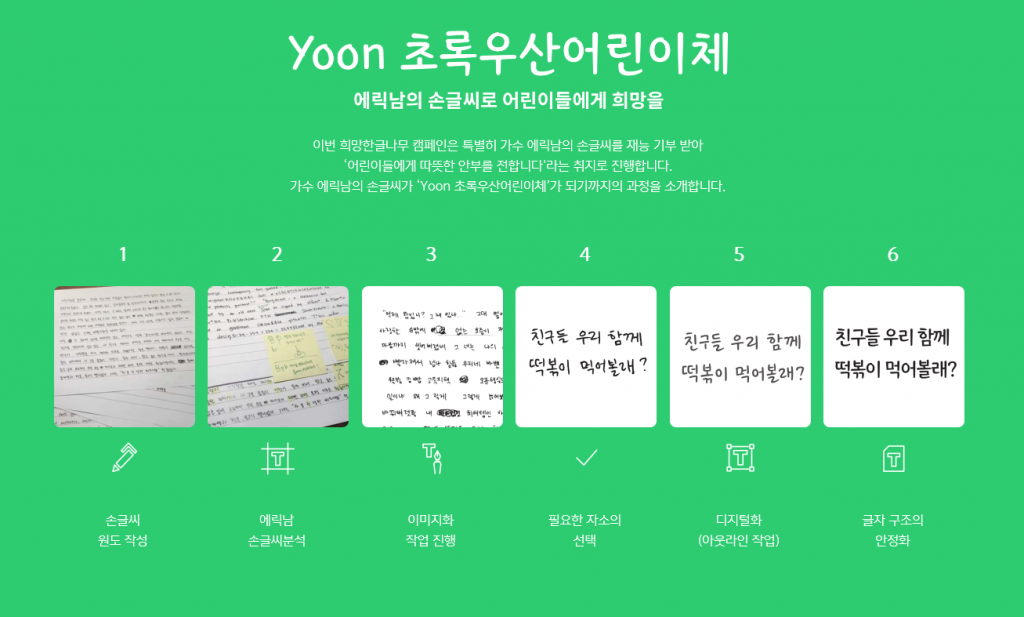
소외 계층에 기부 하고, 예쁜 손글씨 폰트도 받아가고
착한 초록우산어린이재단이 윤디자인그룹과 함께 소외 계층에 기부하면, ‘Yoon초록우산어린이체’를 제공하는 프로젝트를 시작했다. 프로젝트의 이름은 희망한글나무 프로젝트. 윤디자인그룹이 기업의 사회적 책임을 실천하고 한글의 소중함을 되새기기 위해 진행하는 프로젝트다.
이번에 개발한 Yoon초록우산어린이체는 지구촌 소외 계층 어린이들을 후원한 후원자들에게 배포하는 폰트다. 초록우산어린이재단과 함께 공동으로 개발했으며, 폰트의 바탕이 되는 디자인에는 가수 에릭남이 재능기부로 참여했다. 에릭남의 손글씨 원도를 바탕으로 둥근 획 처리에서 어린이가 가진 밝은 이미지를 표현하고, 어린이가 또박또박 집중해서 쓴 듯 반듯한 인상을 갖고 있다.
이번 프로젝트에 앞서 지난 2017년에는 초록우산어린이재단의 후원자인 배우 박보영과 함께 ‘산돌초록우산어린이체’를 제작해 시민들에게 무료 배포하기도 했다.